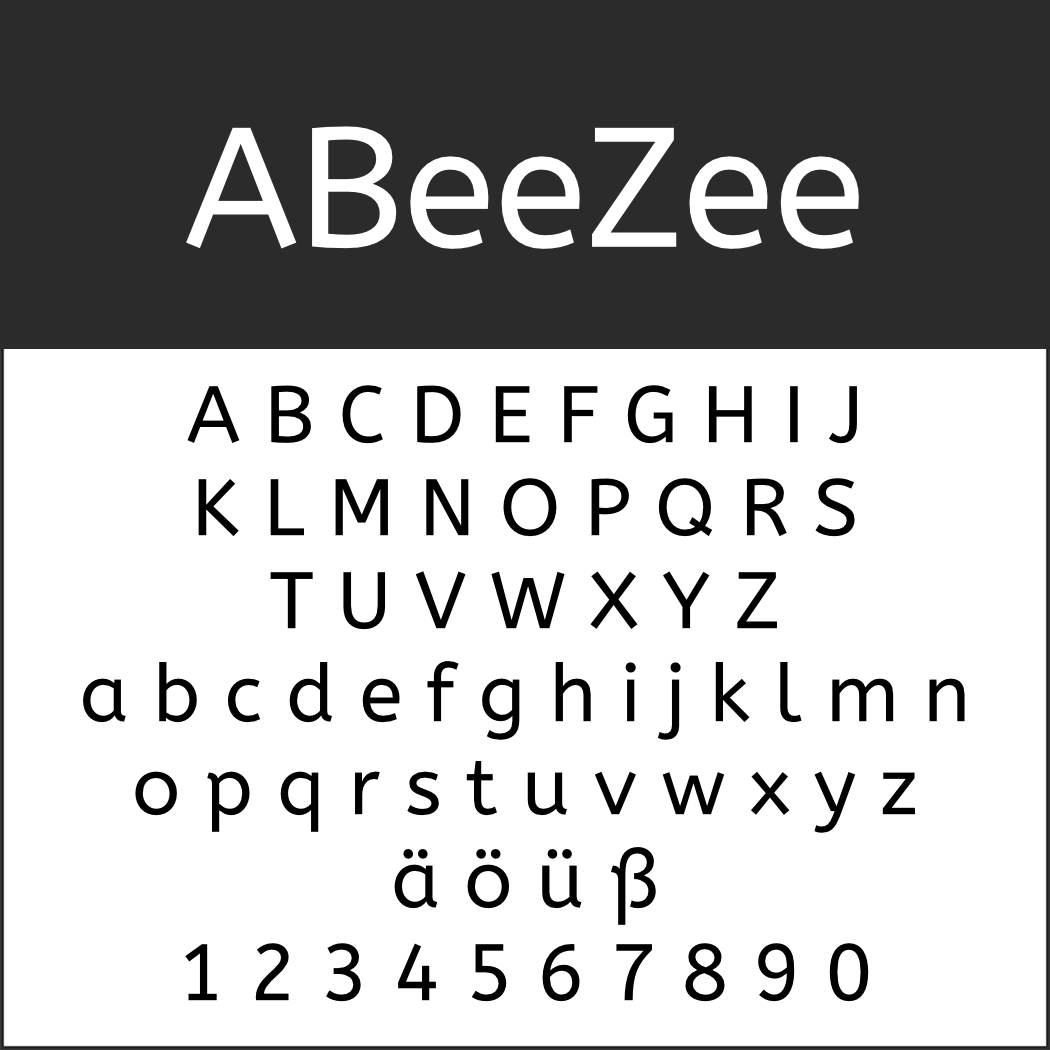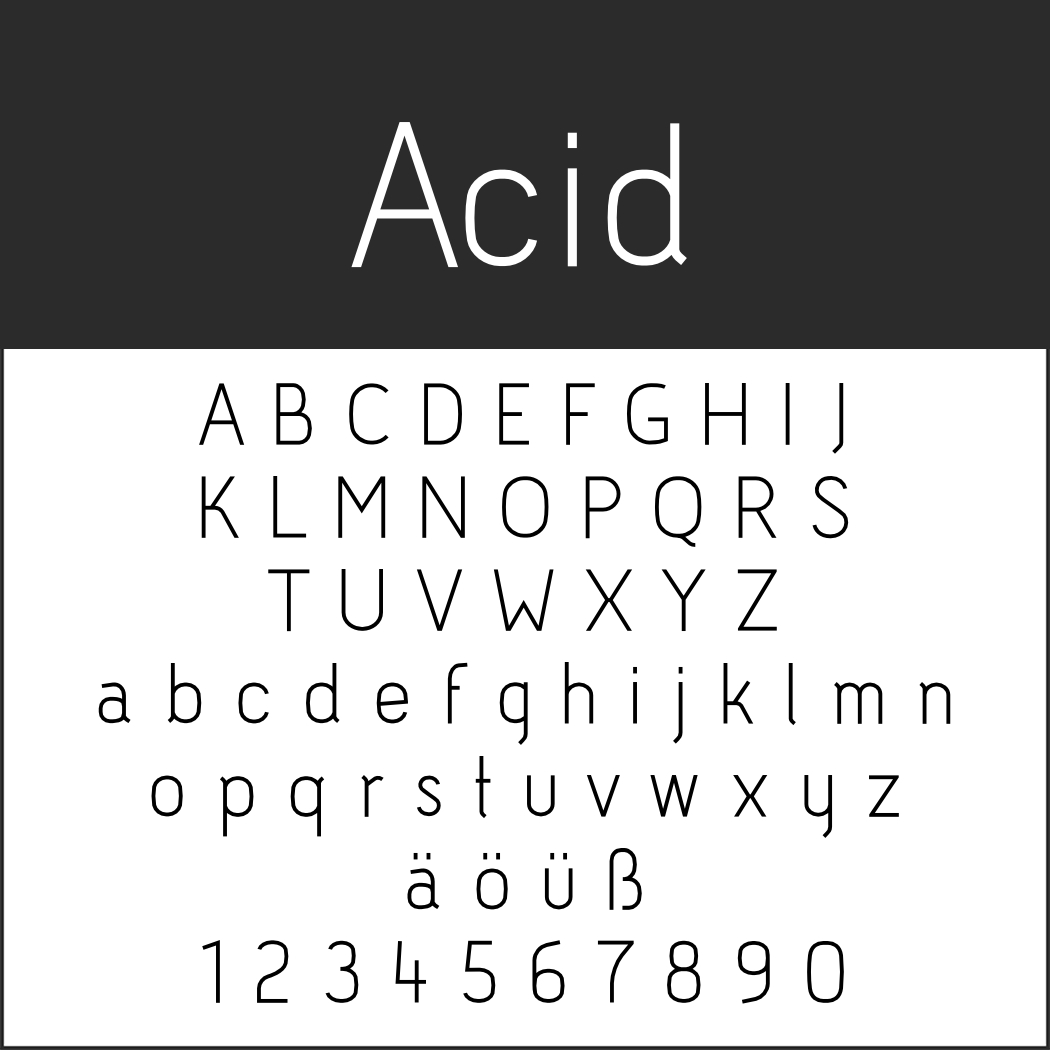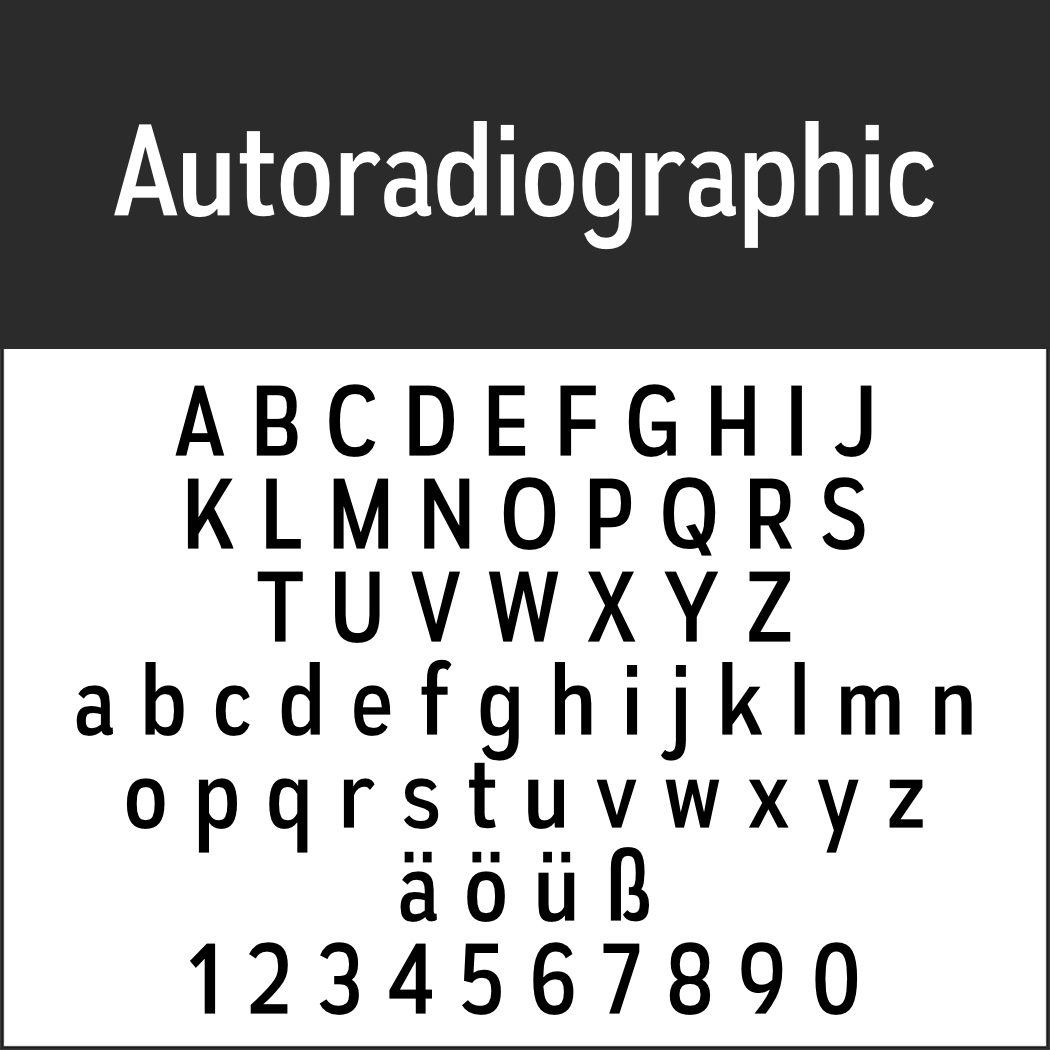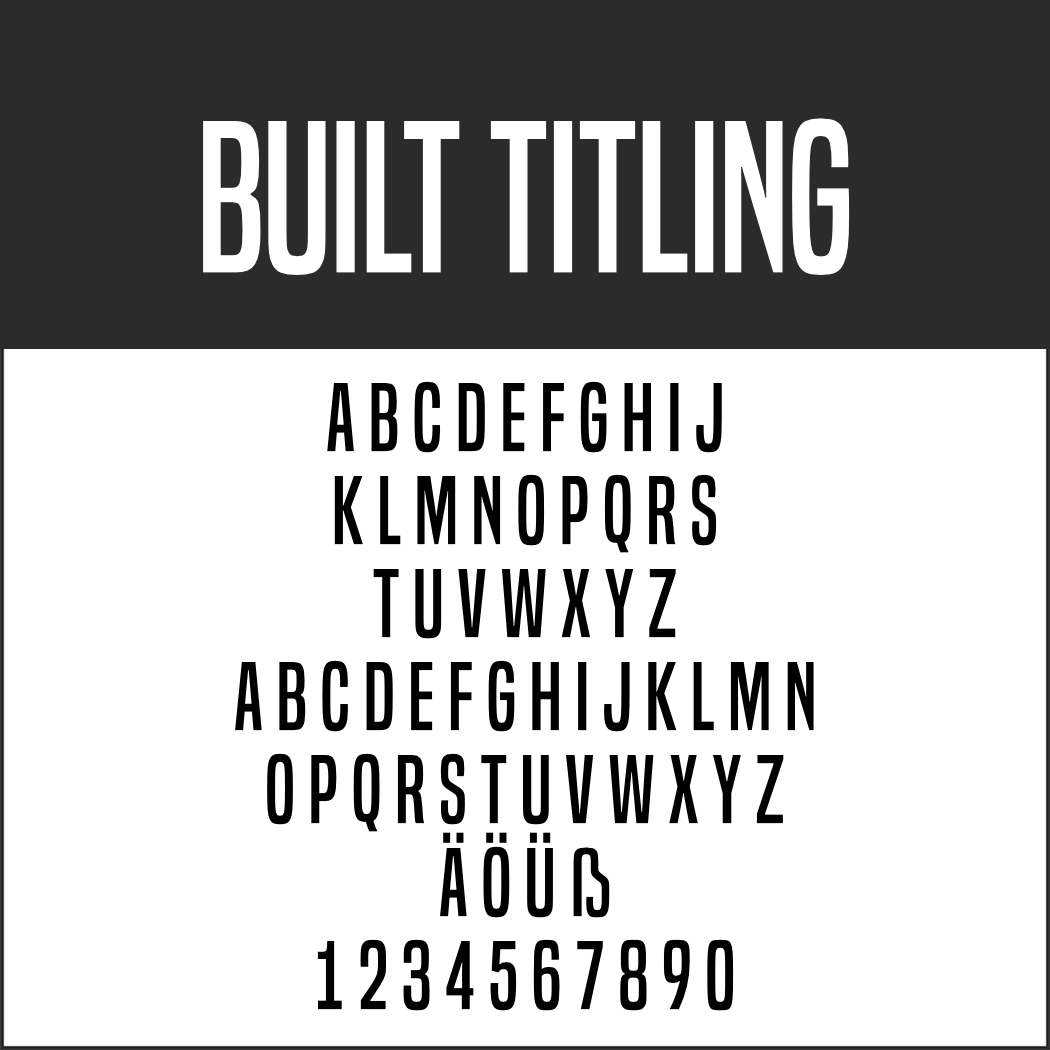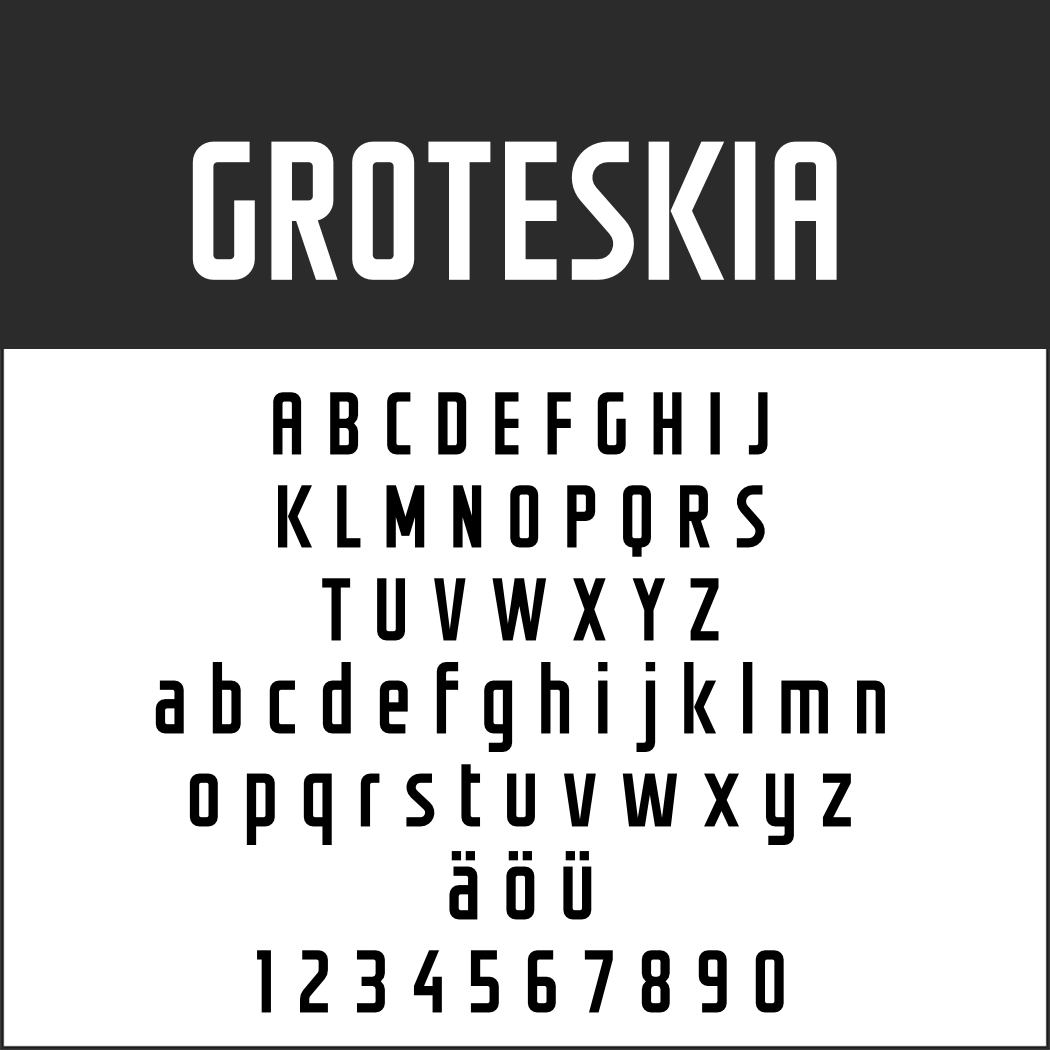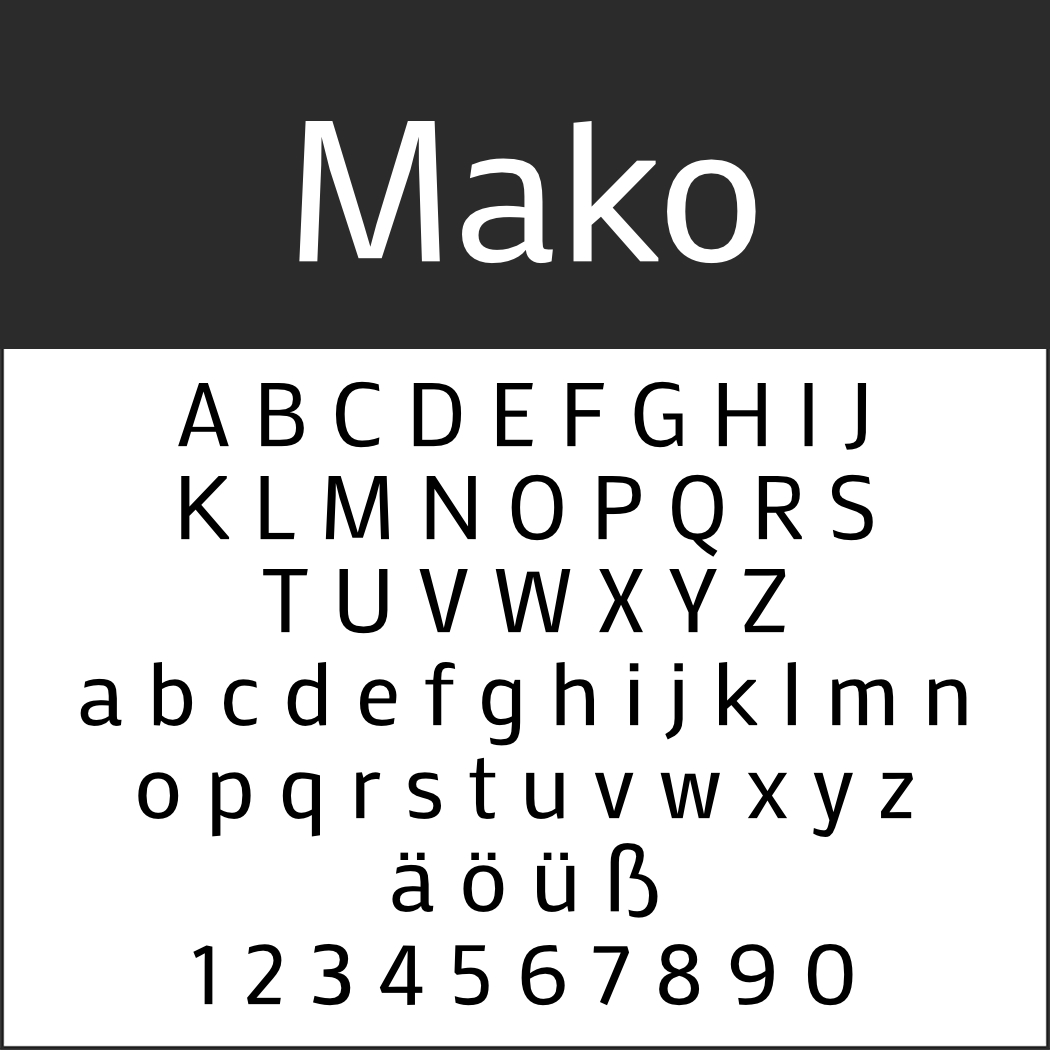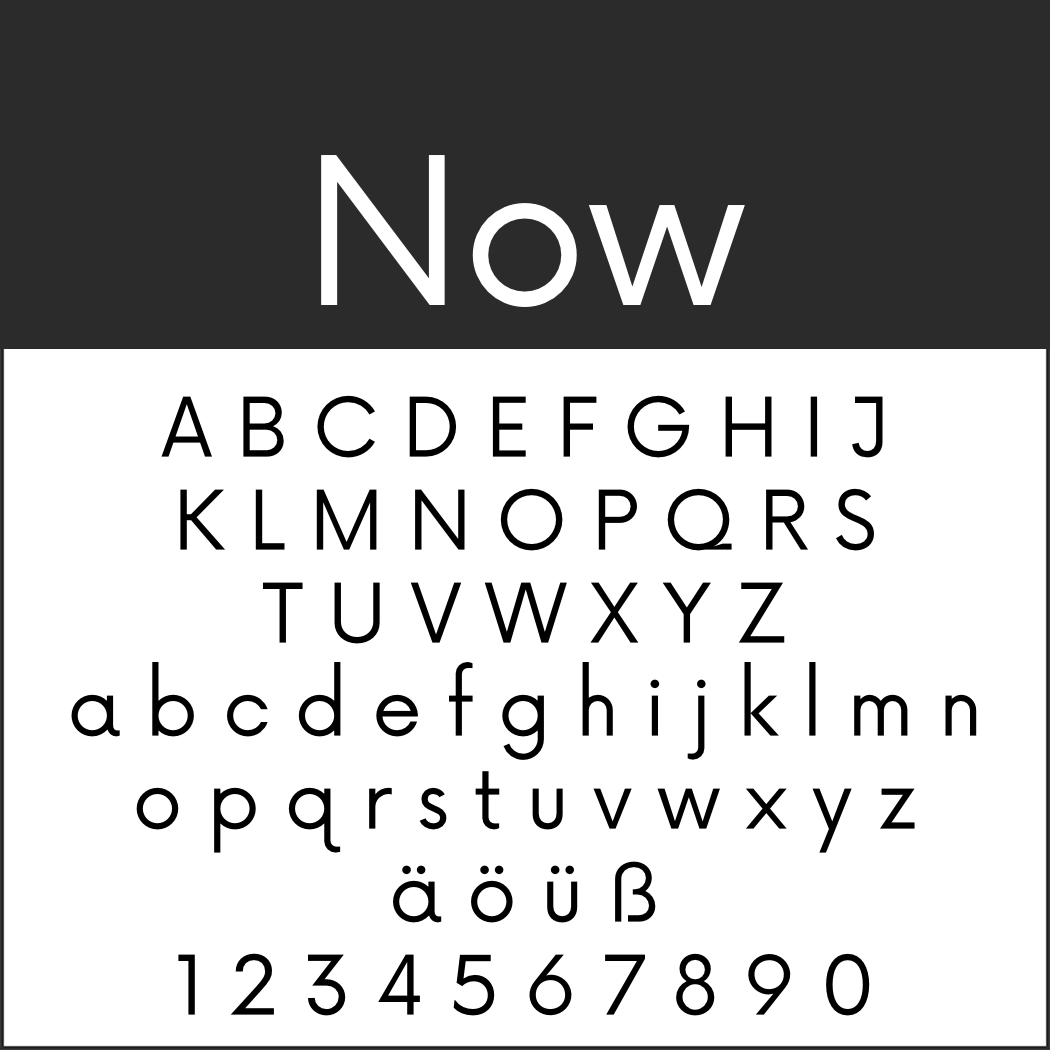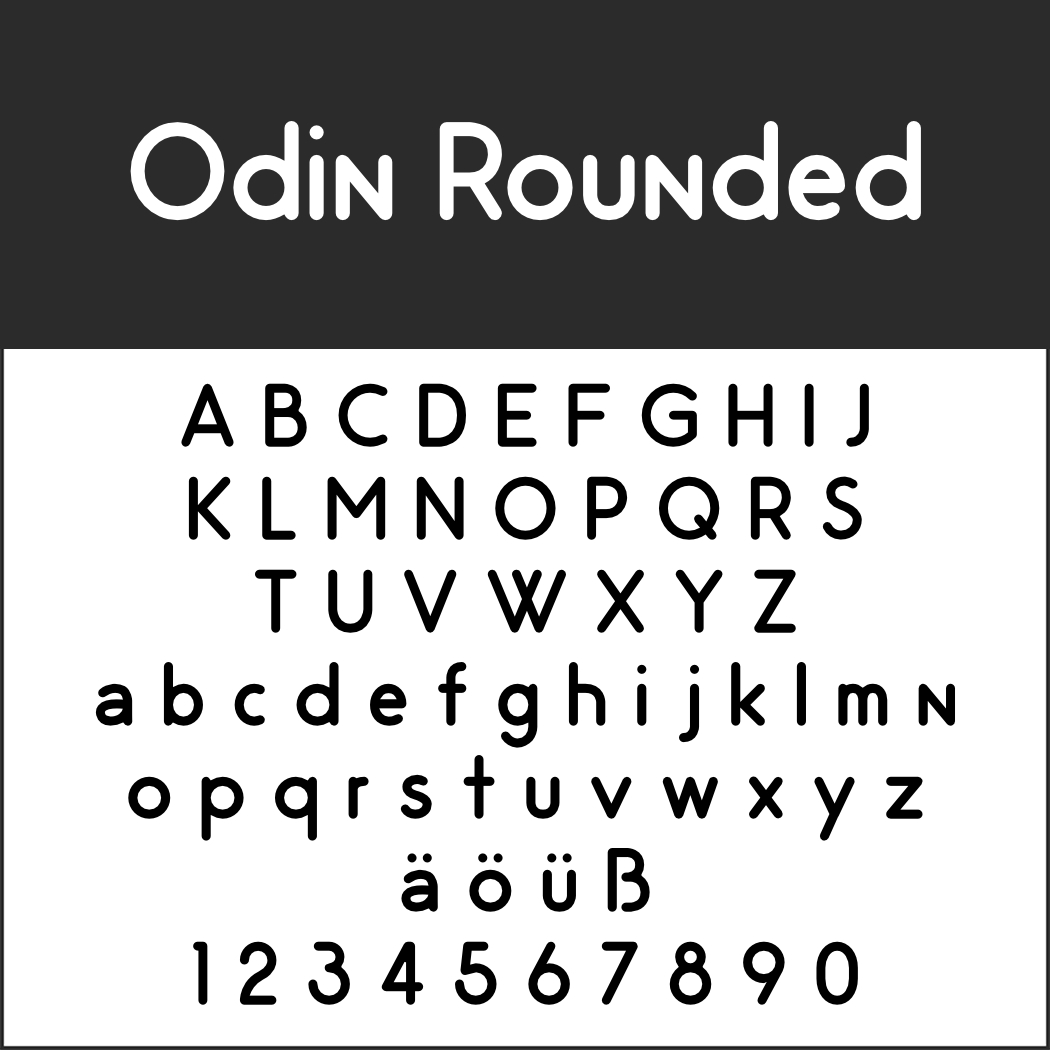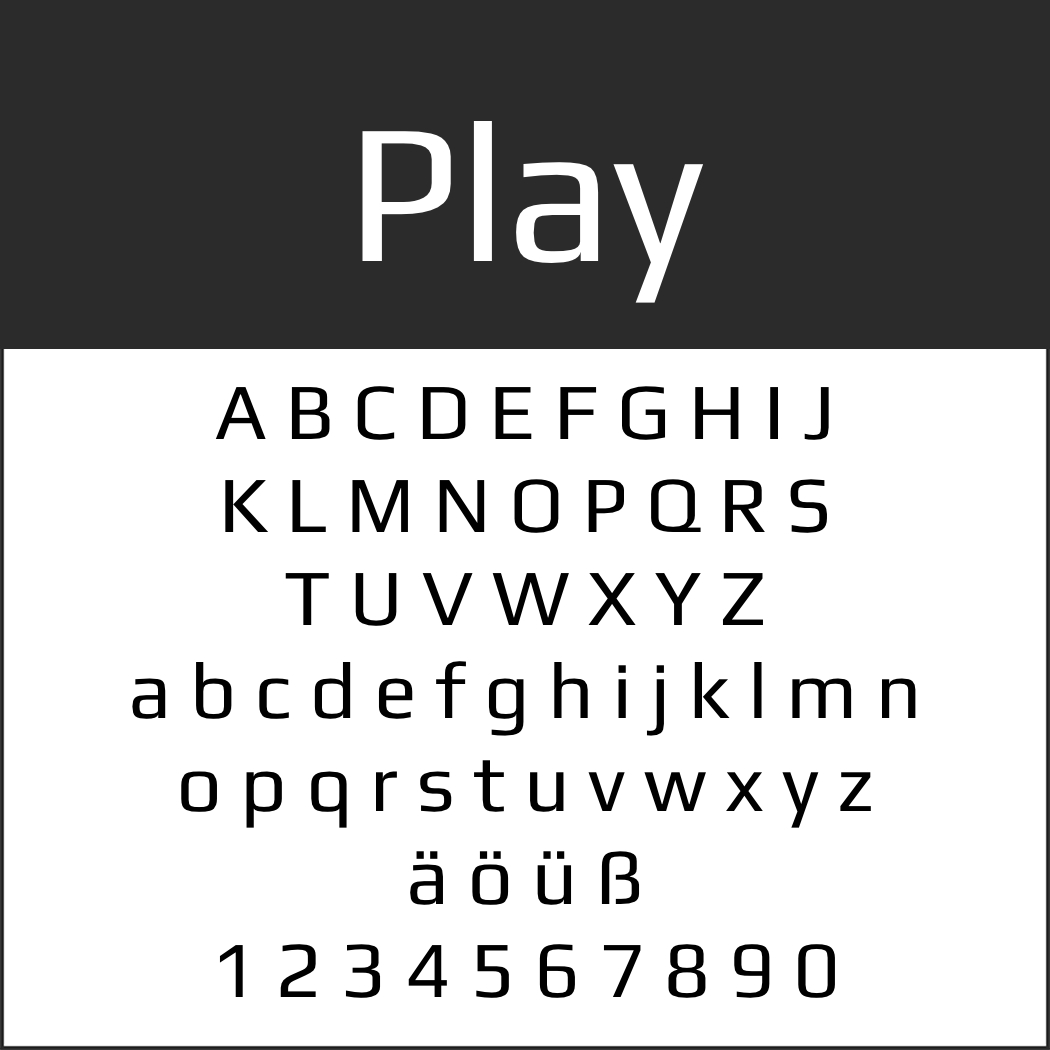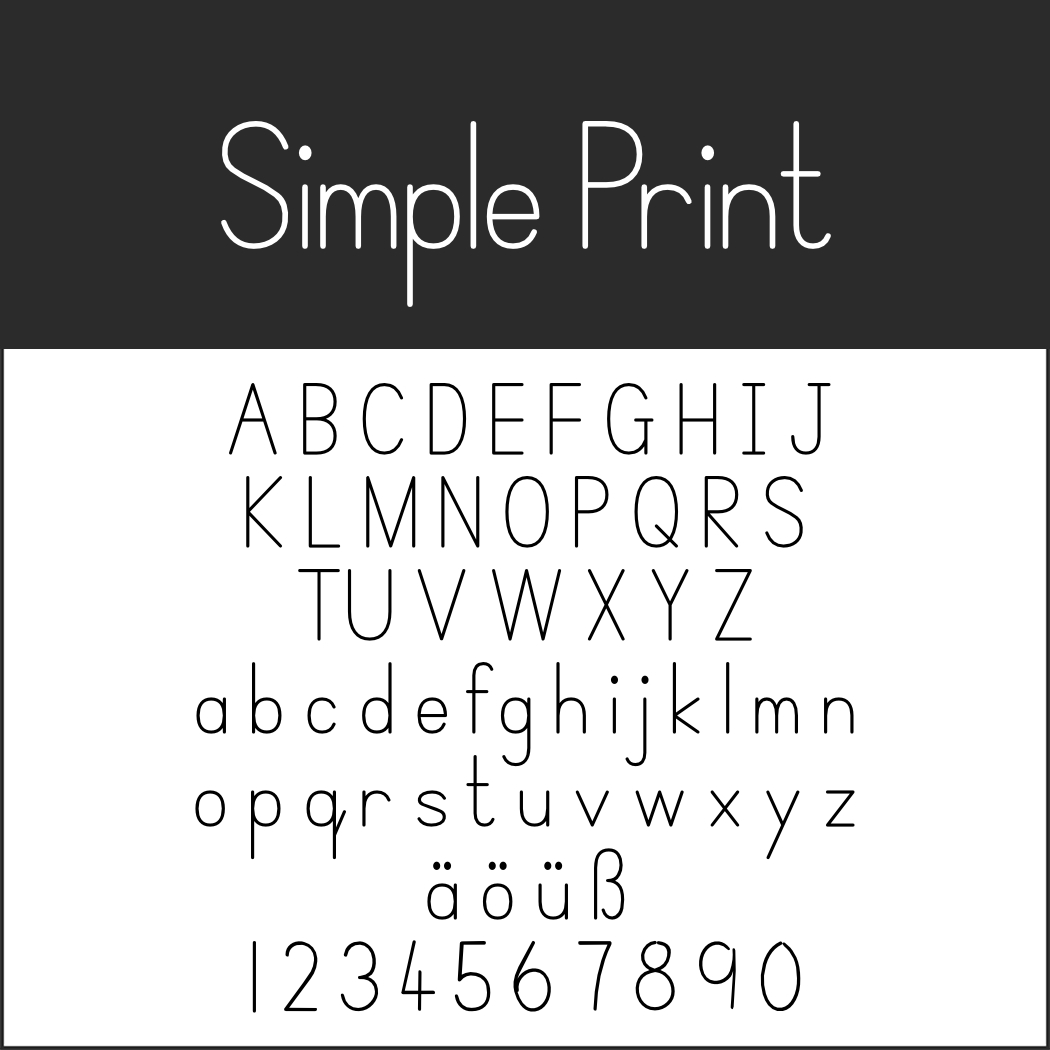
Einfache Schriftarten kommen nie aus der Mode, denn sie sind zeitlos. Deshalb können Sie mit ihnen auch kaum etwas falschmachen. Egal ob textliche Zurückhaltung oder grafisches Understatement — die folgenden Fonts eignen sich für die unterschiedlichsten Anwendungen.
Einfache SchriftartenABeeZee
AbeeZee (ABC) aus Berlin ist eine wahrhaft einfache Schrift. Sie dient Kindern zum Schreibenlernen.
Einfache SchriftartenAcid
Autoradiographic
Die Vorlage für diesen Font findet sich auf Warnschildern aus den 1950er Jahren.
Einfache SchriftartenBuilt Titling
Der Designer hat Built Titling für Überschriften auf Bildschirmen optimiert. Es funktionieren aber auch gedruckte Headlines, nur bei Fließtexten leidet wegen des schmalen Schriftbilds die Lesbarkeit.
Einfache SchriftartenGROTESKIA
Die futuristische Groteskschrift aus Bogotà ist vor allem für kleine Schriftgrade gedacht.
• Besonderheit: kein ß
• Design: Néstor Delgado
Mako
Mako wirkt schlicht und harmonisch, für die Nutzung im Internet freigegeben.
• Design: Vernon Adams
Einfache SchriftartenNow
Der Font von den Philippinen bietet zwölf Schriftschnitte für einen variantenreichen Einsatz.
• Design: Hanken Design Co.
Odin Rounded
Klar und rund — Odin Rounded mit sechs Schriftschnitten wirkt gefällig und dennoch pfiffig.
Einfache SchriftartenPlay
Play wirkt besonders abgerundet, weil der Designer als Grundlage für jeden einzelnen Buchstaben das „O“ herangezogen hat.
• Design: Jonas Hecksher
Simple Print
Simple Print liefert den besten Beweis, dass einfache Schriftarten auch ausnehmend elegant sein können.
Einfache SchriftartenVoces
Das Charakteristische an Voces sind die kurzen Ober- und Unterlängen.
• Design: Ana Paula Megda